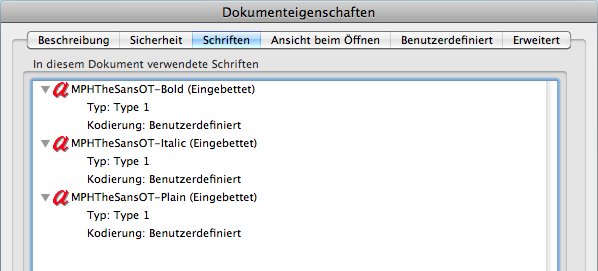
Hausschrift gesucht
die Logotype und die verwendete Typo auf der Startseite ist m.E. die selbe.
Ich habe schon Whatthefont gefragt, aber da gab es keine brauchbaren Tipps.
Vielleicht findet sich unter euch? Bin nicht sooo gut in Schriften erkennen.
Die Seite verwendet die TheSans aber für das Logo haut das nicht hin (»M« zum Beispiel) – evtl. wurde da nochmal selbst Hand angelegt.
auch wenn sie dem kind einen leicht abgewandelten namen gegeben haben: an den buchstaben selbst kann ich in dieser schrift mit dem bloßen auge keine veränderungen feststellen. sogar das ungewöhnliche thesans-›Q‹ ist erhalten geblieben.
und das versale M im Logo? :wink:
Das ist im Logo und nicht im Font.
Warum sollten sie? Sie verwenden es ja nur im Logo …
Gut möglich, aber was soll dann die «eigene» Schrift namens MPHTheSans, wenn offensichtlich nichts verändert wurde?
Evtl. aus lizenzrechtlichen Gründen.
Das nimmt mich wirklich wunder. Kann ich eine besehende Schrift unter anderem Namen lizensieren? Auch wenn keine Veränderungen zur Originalschrift ersichtlich sind?* Wird das günstiger oder warum würde man so was machen?
* Es ist mir klar, dass wir das in diesem Fall nicht ausschließen können.
man macht das bisweilen, um die identi?kation innerhalb des unternehmens mit der neuen schrift zu fördern. wenn die ?rma im schriftnamen drinsteckt, haben mitarbeiter eher das gefühl, dass das ›ihre‹ schrift ist. außerdem verhindert ein eigener name missverständnisse, wenn externe dienstleister die schrift bei der foundry lizenzieren wollen.
Na ja, Du darfst lizenzrechtlich gesehen keine Schrift umbenennen und damit Handel treiben oder sie sonst wie in Umlauf bringen.
Aber ich kenne das Phänomen aus Designagenturen, wo die eigene Hausschrift oft durch einen Namenszusatz markiert wird, um zu verhindern, dass versehentlich eine falsche Schriftvariante gleichen Namens für firmeneigenen Schriftverkehr verwendet wird. In den Agenturen schwirren ja so viele Fontvarianten verschiedener Hersteller durch die Gegend, da passiert leicht mal eine Verwechslung. … Ich könnte mir vorstellen, dass das in anderen Branchen ähnlich gehandhabt wird … :)
sofern die glyphen unverändert sind, wie in diesem fall, wäre das ja egal.
Na ja, das macht schon was aus, weil viele Schriften gleichen Namens aber unterschiedlicher Herkunft eben nicht gleich weit laufen, unterschiedlich gut ausgebaut sind und die Glyphen teilweise auch nicht exakt gleich sind. Deshalb kann es sinnvoll sein, die Hausschrift durch einen Namenszusatz besonders zu kennzeichnen.
Im eingangs gezeigten Beispiel dieses Threads sind die Glyphen ja auch nicht vollständig identisch mit der TheSans; der Buchstabe M unterscheidet sich deutlich.
jein. im logo haben sie das ›M‹ verändert; im ?ießtext konnte zumindest keiner, der sich hier gemeldet hat, die verwendete von der üblichen variante unterscheiden. daher ging es ja hier gerade um schriften, die sich in der form der einzelnen buchstaben und der laufweite nicht (erkennbar) von der für jedermann lizenzierbaren version unterscheiden, aber trotzdem einen eigenen namen haben. in solchen fällen – das wollte ich sagen – ist es dann relativ gleich, ob ich die ABCTheSans, die MPHTheSans oder eben die normale TheSans verwende. wenn der zeichensatz nicht reicht oder ein schnitt fehlt, merkt man es ja.
wenn der zeichensatz nicht reicht oder ein schnitt fehlt, merkt man es ja.
Das hängt wohl auch von der verwendeten Software ab.
Bei mir (Linux/KDE) werden von fast allen Programmen Zeichen der Systemschriften angezeigt, wenn der eigentlich gewählte Font die gewünschten Glyphen nicht selbst bereit stellt. Unterscheiden sich die gewünschte Schrift und die Ersatzschrift nicht allzu sehr, kann der ungeübte Nutzer das schnell übersehen.